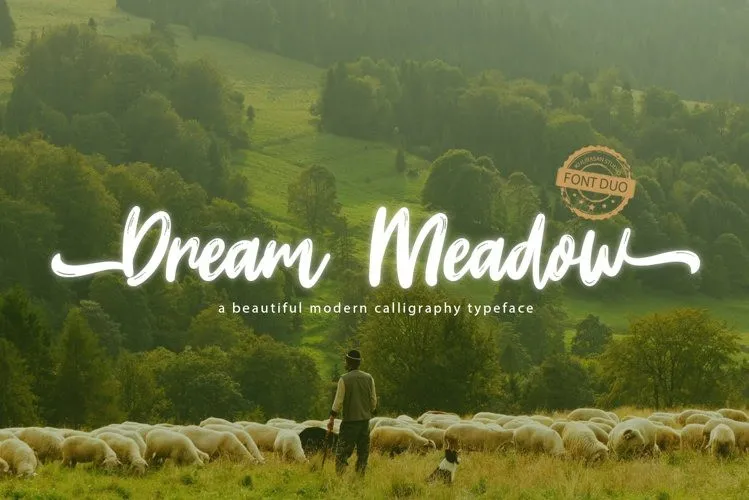
Dream Meadow Brush Font – Download Grátis
Introduzimos a Dream Meadow Brush Font, uma tipografia que captura na perfeição o natural desenho das mãos, rápida e espontânea. Desenhada pelo designer Hamilton e compartilhada pela equipe do khurasan, esta fonte script é descontraída e moderna, oferecendo dois estilos distintos: regular e limpo. Combine os dois para criar resultados incríveis em qualquer projeto de design que você possa desenvolver. A Dream Meadow Script está perfeitamente adaptada para uso em logotipos, identidades corporativas, cartões de agradecimento, faixas informativas ou quaisquer outras criações gráficas que desejar fazer. Esta fonte traz uma vibe leve e divertida que certamente será um acréscimo encantador à sua próxima obra de arte visual.